Europa
Von der Übernahme der römischen Schrift über die zwei Lautverschiebungen bis hin zur heute üblichen Schreibweise — die Schriftgeschichte Europas ist ein Geflecht aus römischen, griechischen und kyrillischen Wurzeln, das sich bis ins Deutsche fortspinnt.
Durch die Ausbreitung des Römischen Reiches gelangte die lateinische Schrift in fast ganz Europa und wurde zur Grundlage der Schrift vieler Sprachen. Doch das lateinische Alphabet allein reichte nicht aus, um alle Laute der jungen europäischen Sprachen abzubilden — es entstanden neue Buchstaben, Doppelbuchstaben und Umlaute.
Im Osten entwickelten die bulgarischen Mönche Kyrill und Method im 9. Jahrhundert eine eigene Schrift für die slawischen Sprachen — sie ist bis heute in Russland, Bulgarien und vielen ehemaligen Staaten der Sowjetunion gebräuchlich. Im Süden lieferte das griechische Alphabet die Buchstaben, die in fast jeder anderen europäischen Schrift wiederzufinden sind.
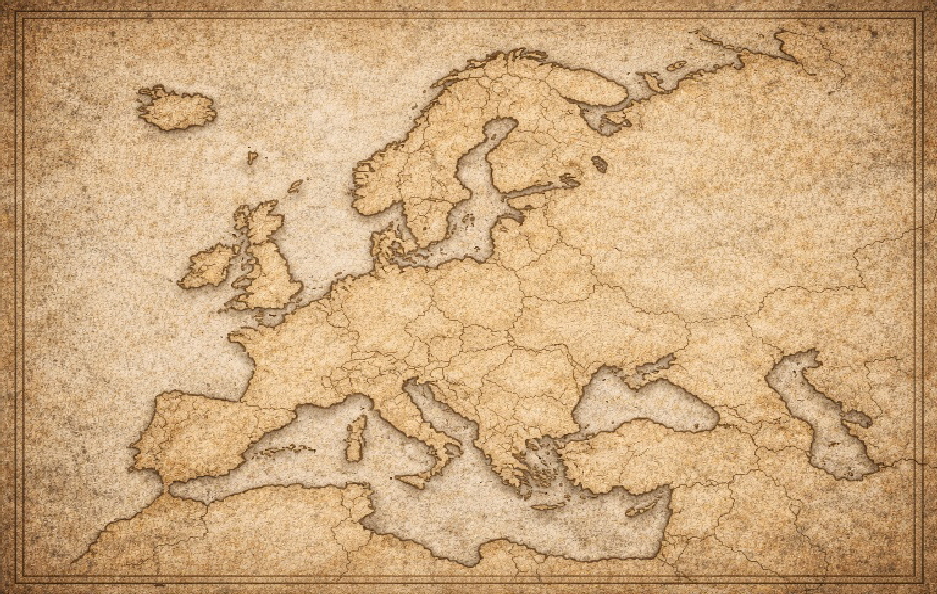
Ein Kontinent — viele Schriften
Europa im Überblick
Karte der Schriftfamilien Europas
Vom Mittelmeer bis zur Ostsee
Drei Schriftfamilien
Lateinisch im Westen, kyrillisch im Osten, griechisch im Süden — Europas Schriftlandschaft erzählt von Reichen, Glaubensgemeinschaften und Sprachen, die sich über Jahrhunderte hinweg gegenseitig beeinflusst haben.